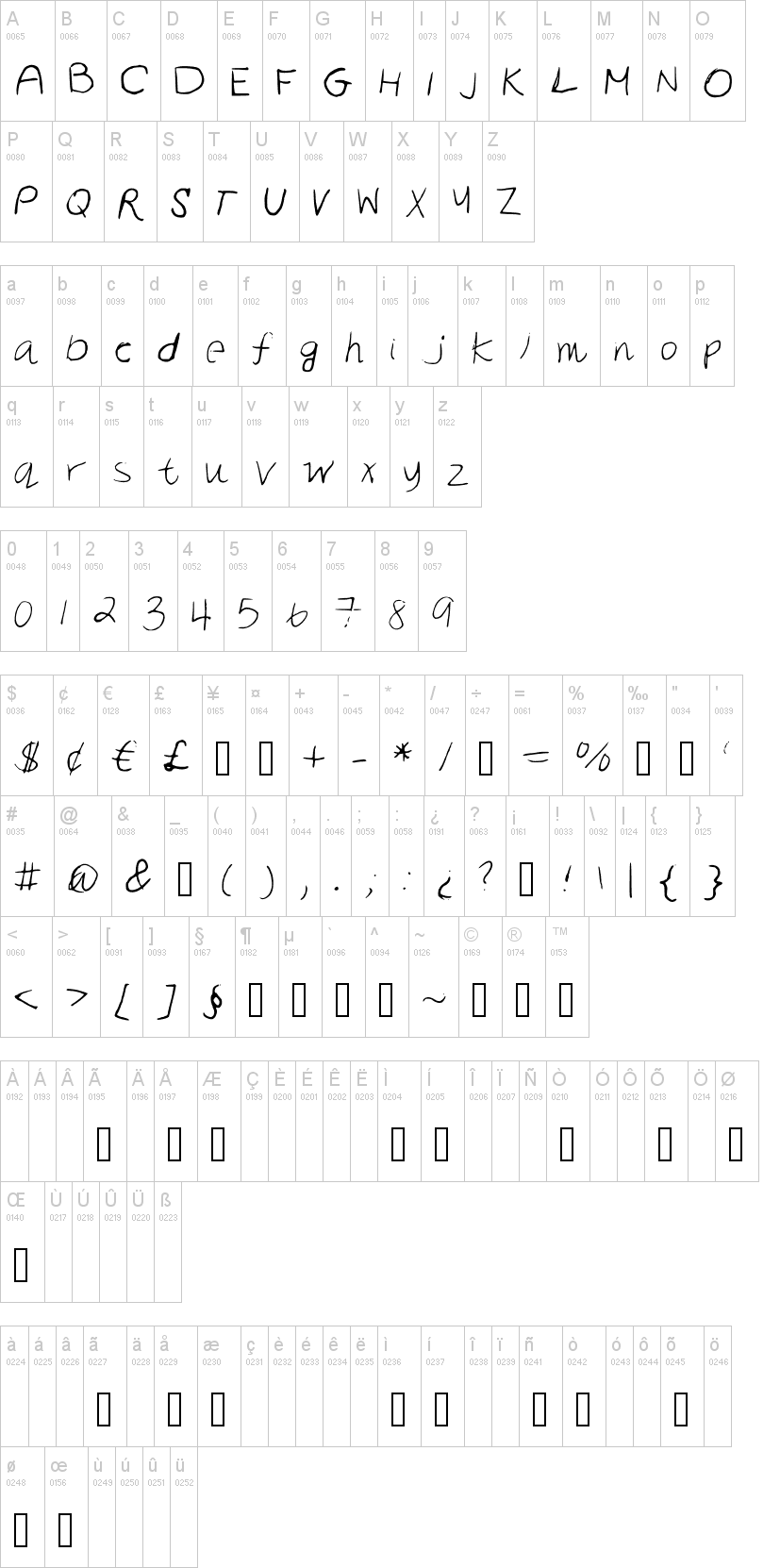
New Day
New Day是一款简洁、优雅的英文字体,由英国设计师Andrew Footit设计,它的每一个字母都拥有着自己的特点,在使用时会给人以温柔、舒适的感觉。New Day字体的字符具有清晰的结构,在设计时也考虑了节奏感和空间的关系,使得它的表现力更加丰富,能够更好地表达文字的意义。New Day字体适用于海报、书籍、标识等设计,能够表现出文字的灵动与细腻,让文字更加精致优雅。
New Day是一款非常不错的手写艺术字体,具有很好的视觉感,适合于文化类的宣传设计、商业类品牌的广告和产品包装设计以及个性化文字排版等较多场景。
New Day字符映射图